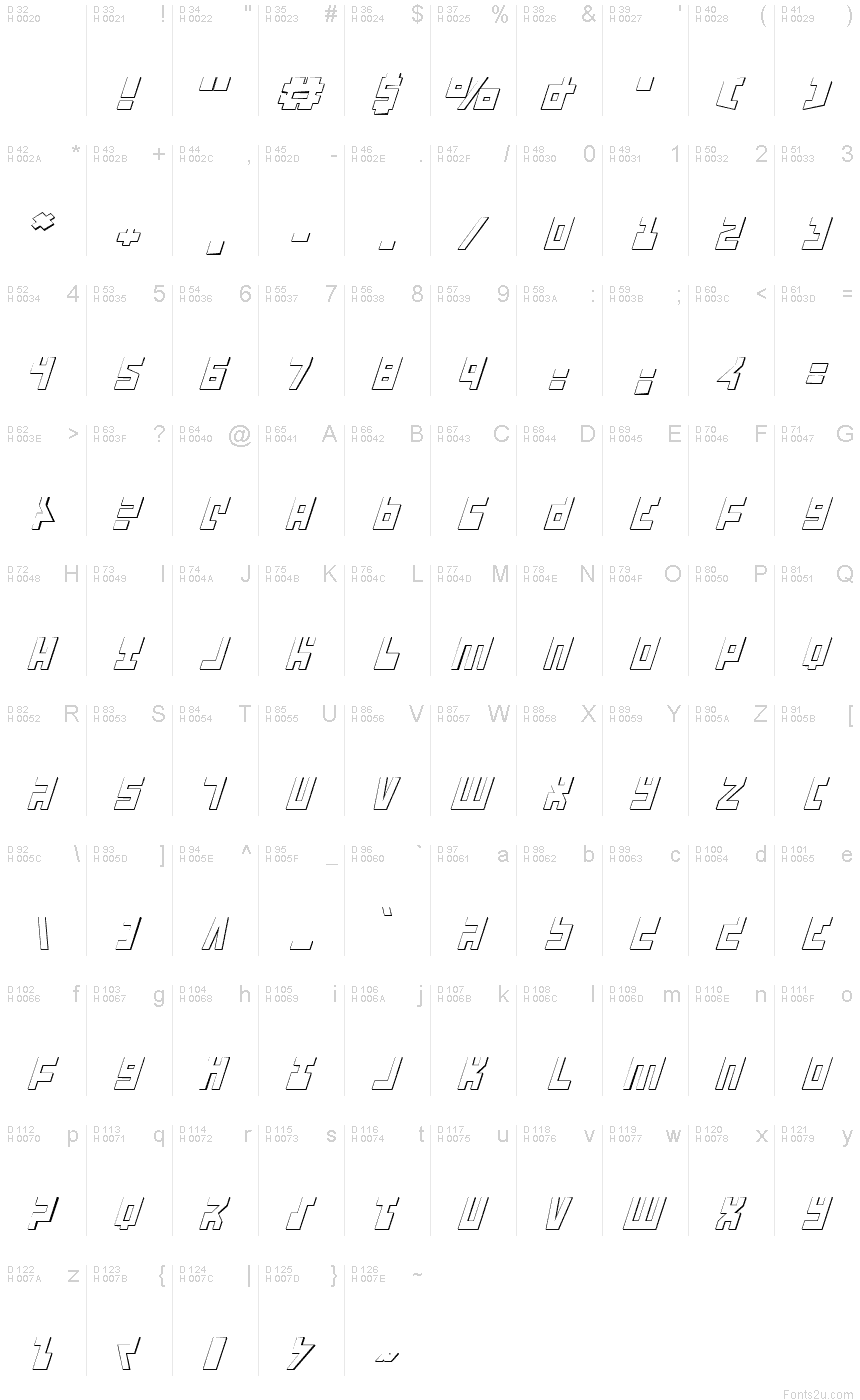
UFO Hunter 3D Italic di Iconian Fonts è un carattere display contornato e futuristico, disponibile gratuitamente. Le sue lettere ampie e squadrate sono fortemente inclinate in avanti, con angoli smussati e linee interne che ricordano i pannelli metallici sovrapposti dello scafo di un'astronave.
Le schermate dei titoli dei videogiochi rappresentano il suo contesto ideale, in particolare per sparatutto arcade, giochi di corse e altri titoli dal ritmo incalzante. La struttura a contorno può valorizzare anche il branding per gli e-sport, i poster di fantascienza e il merchandising, dove la silhouette angolare richiama i pannelli dei veicoli, i contrassegni delle navicelle e le decalcomanie tecniche. In tutti questi ambiti, la tipografia diventa parte integrante dei macchinari e dell'azione anziché un semplice testo, risultando particolarmente adatta all'intrattenimento futuristico.